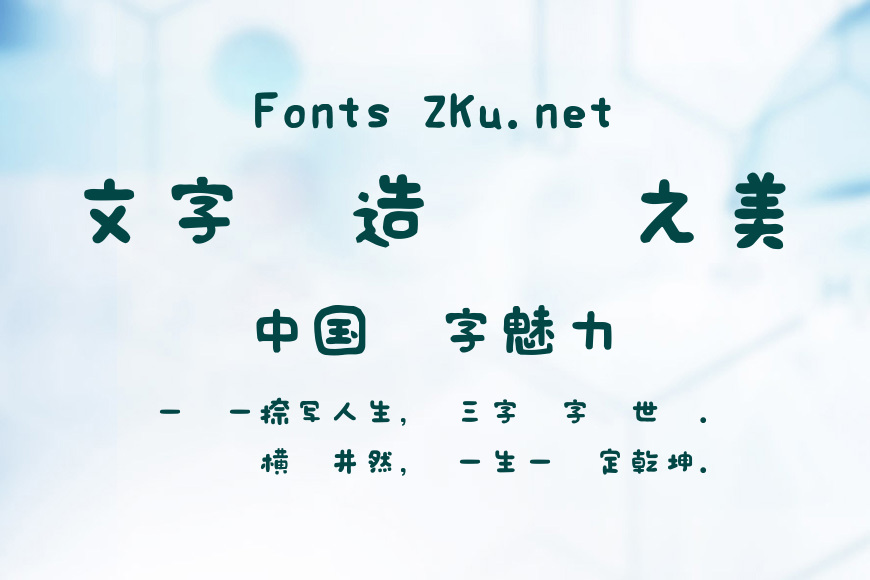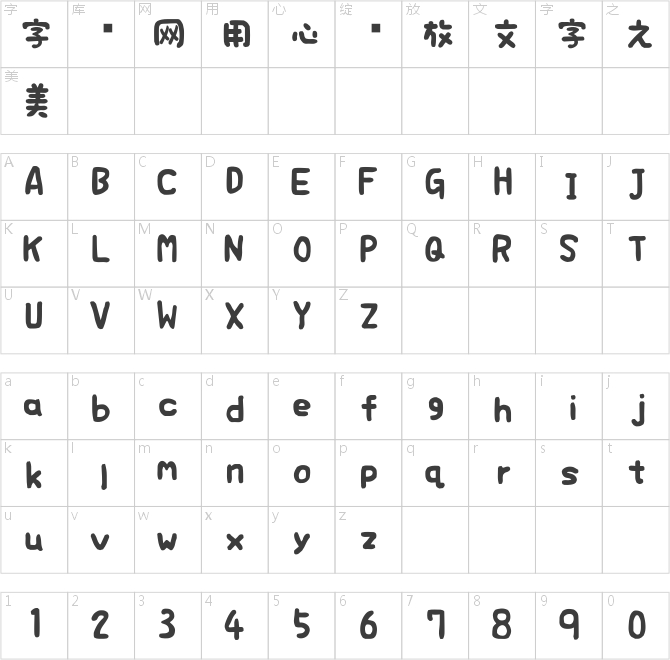
字体名称: 豆豆字体えるま
作者版权: 隠れ家
豆豆字体えるまー
えるまーフォント<等幅> ver.1.60
えるまーPフォント<プロポーショナル> ver1.60
マジックペンで書いたような手書きフォントです。<第二水準まで>
足跡やハート等が罫線の後半に入っています。「けいせん」を変換させてみてください。